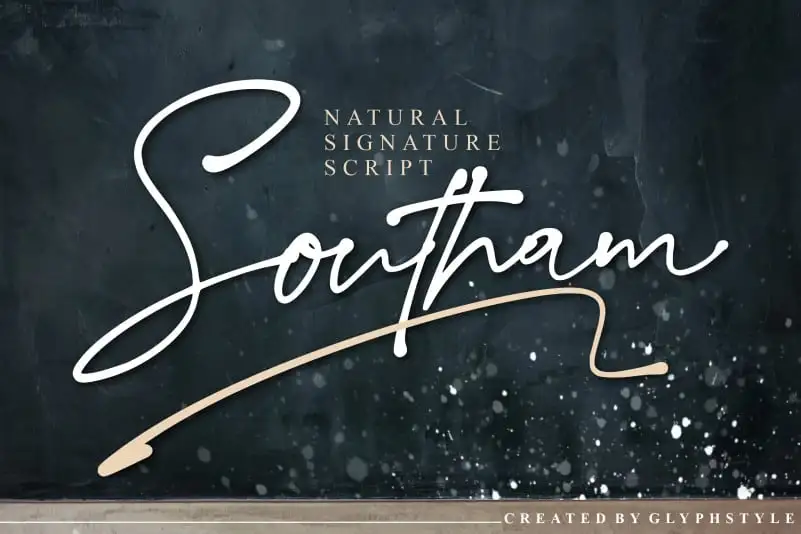
Southam Natural Script Font – Download Grátis
A Southam Natural Script Font é uma maneira perfeita para dar um toque especial a qualquer projeto visual. Ela evoca textos assinados com estilo de caneta e deslizamento natural, criando uma aparência elegante que captura o senso de arte na própria mão do designer. Esta fonte de autógrafos é perfeitamente adaptada para diversos usos, como gráficos de entrevistas, cartões de visita, logos de produtos ou até mesmo marcas d’água e identificações visuais para eventos de casamento. A Southam Natural Script Font é a escolha ideal quando você deseja transmitir um toque sofisticado e criativo em seu próximo projeto visual.